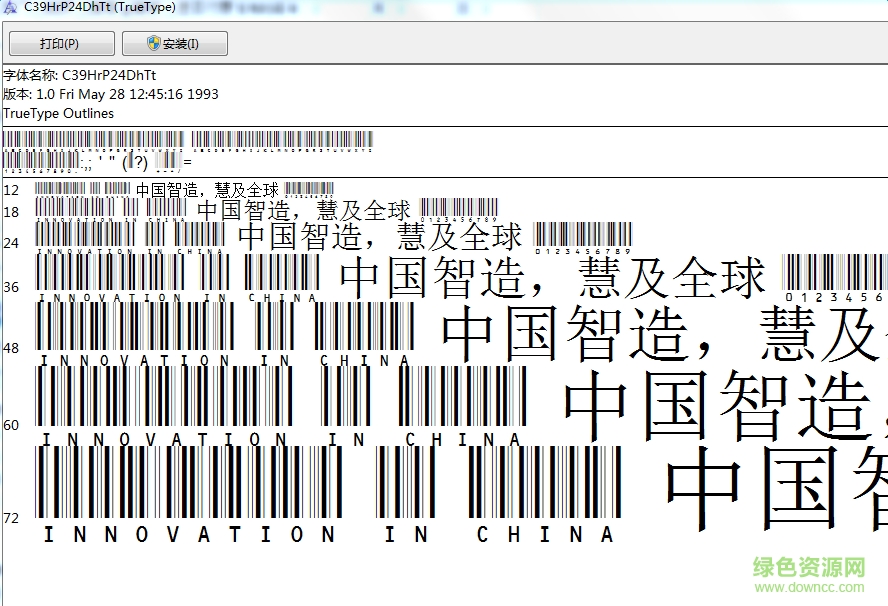
c39hrp24dhtt条码字体
c39hrp24dhtt条码字体是一款c39hrp24dhtt下载条码字体,专门为用户打造的数字和字母转换条形码字体的条码字体,小编亲测可用,您还在等什么?喜欢就来下载体验呗!
字体介绍:
C39HrP24DhTt.ttf(条型码字体),可以将输入的数学或字母转换成带有条型码的数字和字母。